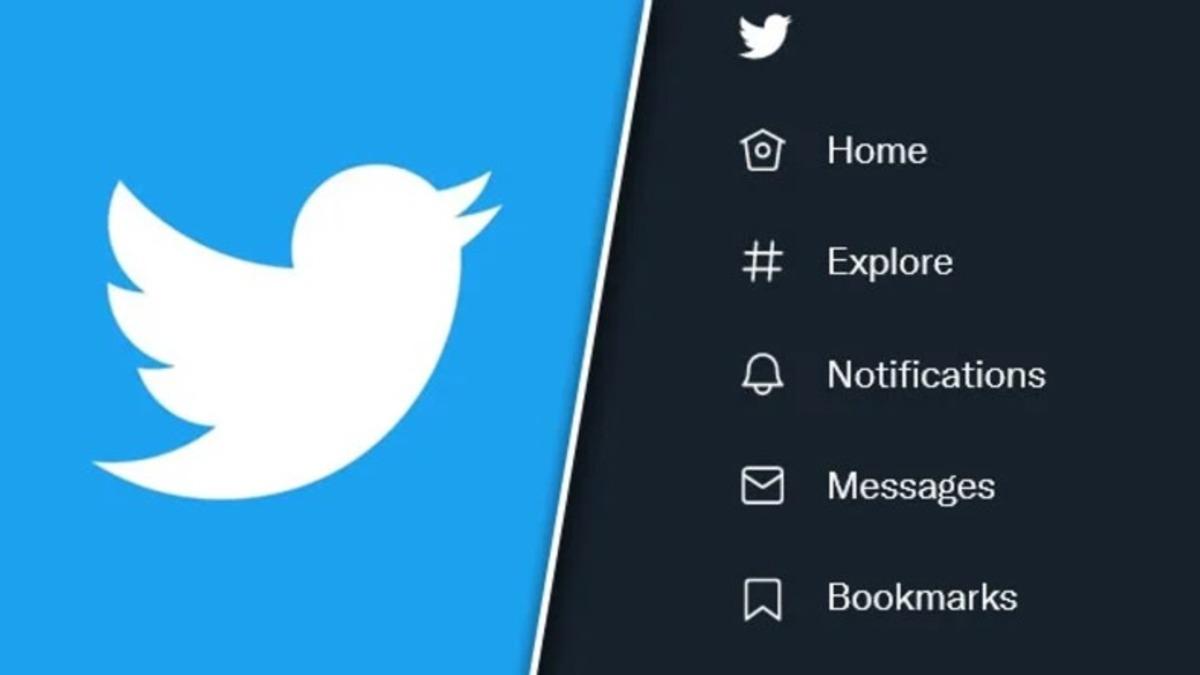
Sosyal medyanın en çok kullanılan platformlarından birisi olan Twitter, geçtiğimiz günlerde radikal bir karar alarak platformda kullanılan fontu tamamen değiştirdi. Chirp fontunu kullancıların beğenisine sunan platform, aynı zamanda daha yüksek kontrast içeren tasarımıyla birlikte büyük ses getirdi.
Twitter'ın yapmış olduğu bu değişiklik, çoğu kişi tarafından beğenilmedi ve şirketin Erişebilirlik Merkezi'ne iletilen şikayetlere göre bu yeni fontun, kullanıcılarda baş ağrısına yol açtığı ortaya çıktı. Ayrıca, sitedeki yeni tasarımın yüksek kontrast seviyelerinde olmasının da engelli bireylerin işini zorlaştırdığı belirtildi.
Twitter, sorun devam ederse gelecekte değişiklikler yapmaya söz verdi
ABD’nin Web İçeriği Erişilebilirlik Yönergeleri (WCAG) kurumu, engelli bireylerin sosyal medya platfomlarını rahat bir şekilde kullanabilmesi için uygun bir kontrast aralığı belirliyor. Birçok sosyal medya platformu bu kontrastlara uysa da Twitter'in geçtiğimiz günlerde kullanıcılarına sunduğu yeni tasarımın, kurumun belirlemiş olduğu kontrast seviyelerinin çok üzerinde olduğu ortaya çıktı.
Uzun yıllardır Helvetica fontunu kullanan Twitter, yüksek kontrastlara sahip yeni tasarımıyla birlikte yeni fontu Chirp'ü de kullanıcılarının beğenisine sundu. Yeni font birçok kişi tarafından tam puan almayı başarsa da onlarca kullanıcı, yeni fontun gözlerini inanılmaz derecede yorduğunu, dolayısıyla baş ağrısına yol açtığını duyusal engelleri bulunan insanların yazıları okumada epey güçlük çektiğini dile getirdi.